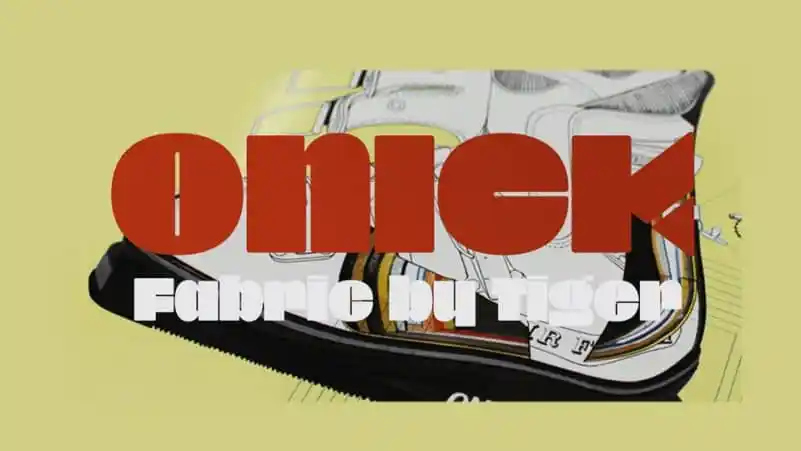
A Onick Display Font é uma opção perfeita para aqueles buscando um design poderoso e dinâmico. Com espaçamento apertado e formas grandes, ela atende bem a qualquer aplicação de tamanhos acima de 72 pontos. Ideal tanto para headlines impactantes quanto para materiais como postais, revistas ou capas, essa fonte expressa uma determinação indomável e um ar robusto, que poderia ser comparada à durabilidade de um parafuso. Desenvolvida pelo talentoso designer Dharma Type, a Onick Display se destaca pela sua simplicidade e força. Com uma gama completa de caracteres, incluindo suporte para múltiplas línguas, ela oferece tudo o que você precisa para criar visuais atraentes e bem-sucedidos em seus projetos gráficos criativos. Seja para capitar a atenção do público em seu site ou em um poster impactante, essa fonte é uma escolha ideal. Ela destaca-se como uma opção de tipo free heavy and contrast, proporcionando resultados visuais impressionantes e inovadores que se destacam em qualquer projeto.